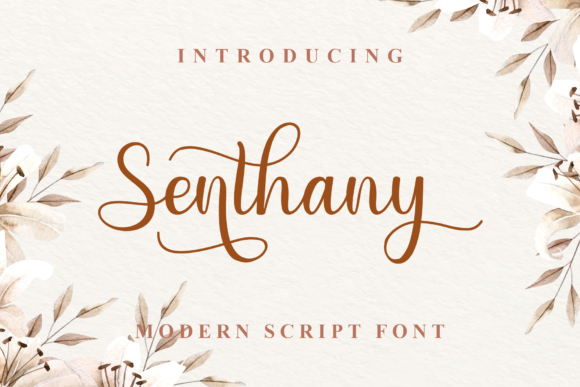
Senthany
Senthany์™€ ๊ฐ™์€ ๊ณ ํ’ˆ์งˆ ์ž์‚ฐ์„ ์ฐพ๊ณ  ์žˆ๋‹ค๋ฉด ์ด ํ”„๋ฆฌ๋ฏธ์—„ ํŒจํ‚ค์ง€๋Š” ์ฐฝ์˜์ ์ธ ํ”„๋กœ์ ํŠธ๋ฅผ ์œ„ํ•œ ํ™˜์ƒ์ ์ธ ์„ ํƒ์ž…๋‹ˆ๋‹ค.
POD(์ฃผ๋ฌธํ˜• ์ธ์‡„) ์ œํ’ˆ, ๊ฒฐํ˜ผ์‹ ์ดˆ๋Œ€์žฅ ๋˜๋Š” ์†Œ์…œ ๋ฏธ๋””์–ด ๊ทธ๋ž˜ํ”ฝ์„ ๋งŒ๋“ค ๋•Œ Senthany๋Š” ์ด์ƒ์ ์ธ ์„ ํƒ์ž…๋‹ˆ๋‹ค.